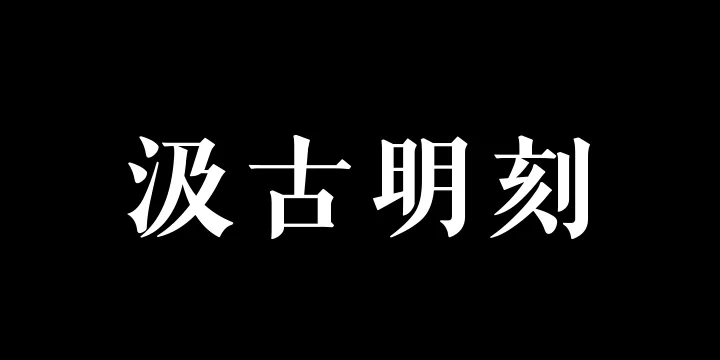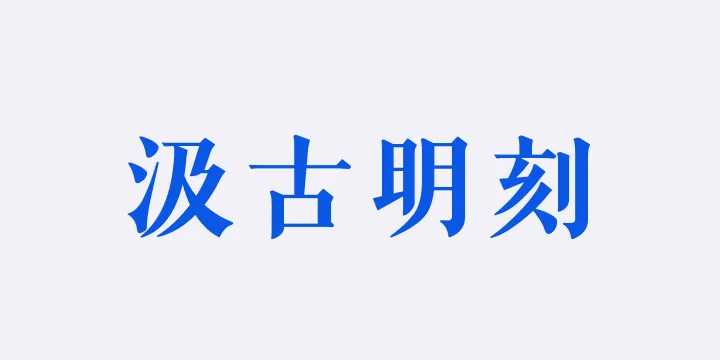
字体简介: 山海汲古明刻(雅致版),是一款全新的字体,包含汉字6763个,符号200+个,一款国风复古刻本字体。该字体字形秉承中国古代古籍善本之字形特性,版刻刀法剔透,字形方正,端庄严谨,古朴大方。在饱有笔墨之意的同时,又突显刀刻之美,笔刀结合刚柔并济。在秉承笔形间创新,结合当代设计视觉环境,融入现代审美,适用场景更多元,笔画造型清新雅致,删繁取简,粗细对比强烈,重现雕版字体的古韵之美。